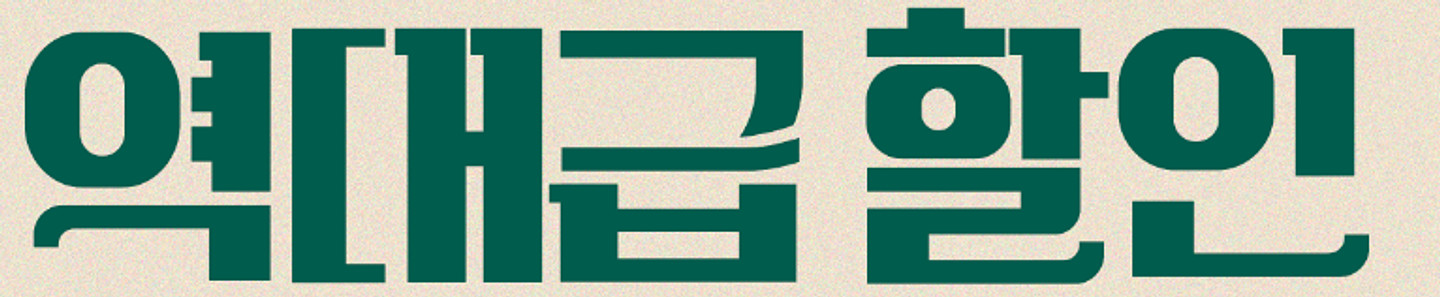
연필의 정석 아님 연필고딕그레이랑 비슷한데 그 둘보다 더 고딕인 느낌이에요ㅠㅠ 많이 본 폰트인데 이름이 기억 안 나요 ㅠㅠ 고수님들 부탁드려요ㅠㅠ 흑흑
폰트 궁금합니다ㅠㅠㅠ 해당 폰트 뭔지 아시는 분 계실까요?
폰트 검색해도 비슷한 글꼴만 나오고 확실하게 안 나오던데 혹시 무슨 폰트인지 아시는 분 계실까요?
이 폰트나 이거랑 비슷한 거 무료로 있을까요?
혹시 이거 무슨 폰트일까요??ㅠㅠ
폰트 명이 뭘까요?
짜잔씨님 유튜브에 있는 폰트 궁금해요“”
이미지찾기로 안나오네요 ㅠㅠ 부탁드려요
archive 폰트 궁금해요!
황보당 글씨체 알려주세요 감사합니다
이 폰트 무엇인가요?
이 폰트가 뭘까요?
메인 타이틀 [설레는 봄쿠폰] 폰트가 궁금합니다.
이폰트 뭐에요?
"세컨핸드 패션위크" 에 쓰인 폰트 무슨 폰트일까요?
혹시 이거 무슨 폰트인지 아시나요? ㅠㅠ 카톡 폰트 바꿨는데 도저히 못찾겠어요..